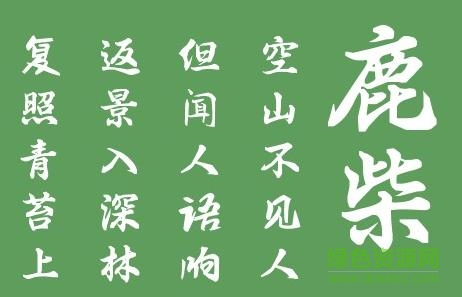
葉根友離賢行書(shū)字體
葉根友離賢行書(shū)字體是葉根友的最新字體作品,將行書(shū)的氣、意、形體完美表達(dá)出來(lái),作為字帖適用是非常合適的。歡迎大家來(lái)綠色資源網(wǎng)踴躍下載使用!
葉根友離賢行書(shū)
葉根友離賢行書(shū)有一種輕描淡寫(xiě)的韻味,非常的文雅好看,大氣而又自然流暢是這款字體的主要風(fēng)格。